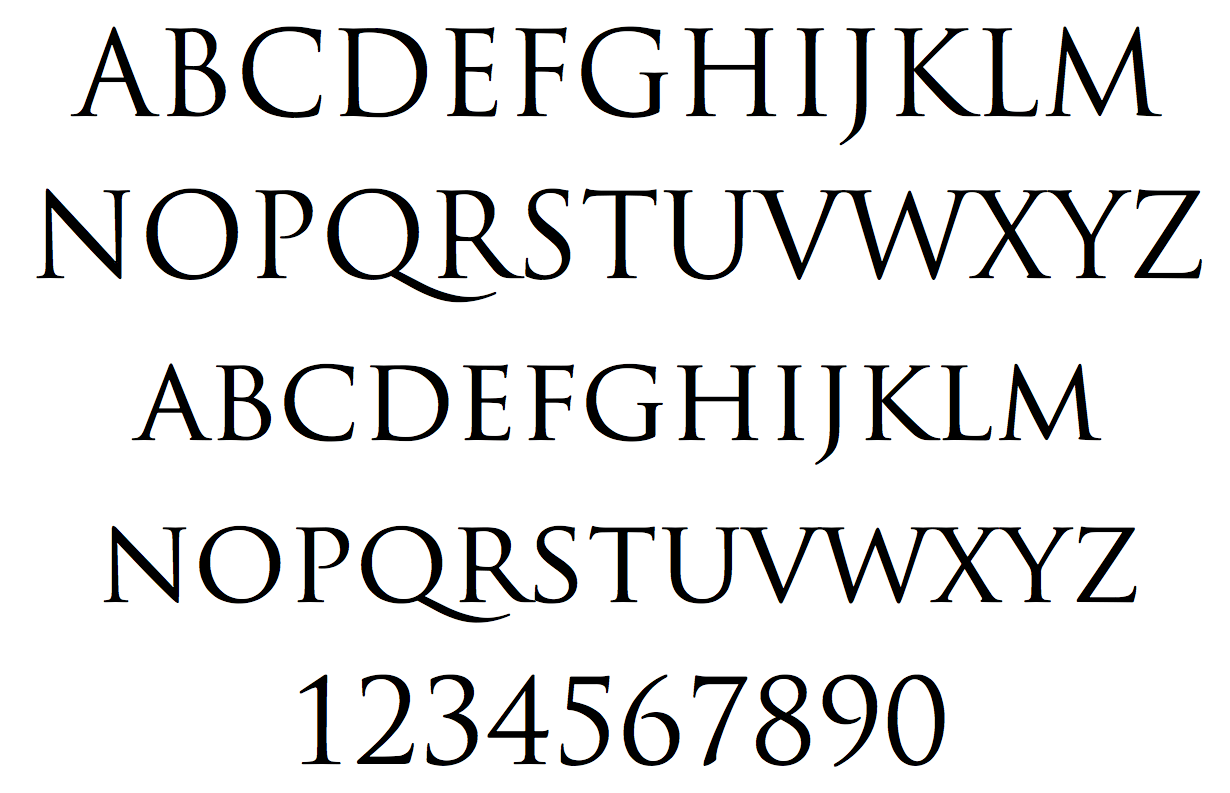
Borsok
Источник: vk.comАкцидентный шрифт от киргизского дизайнера Dastan Miraj
Ossem
Источник: vk.comГротеск в четырёх начертаниях, включающее обычное, округлое, грубое и ржавое начертания. Разработчик: Typedepot
Belepotan
Источник: vk.comАкцидентный шрифт, имитирующий написание кистью
Tangak
comАкцидентный шрифт от дизайнера Dastan Miraj
Cormac
Источник: vk.comГуманистический гротеск в двух начертаниях. Разработан в Typedepot
Akrobat
Источник: vk.comСовременный шрифт без засечек с сокращёнными пропорциями. Включает 8 начертаний, стилистические альтернативы, локализованные формы, табличные цифры. Разработчик: Fontfabric
Pomidorko
Источник: vk.comКириллический шрифт, который изначально создавался для оформления ютуб-канала PomidorKo. Автор: Тони Сидачова (Киев, Украина)
Exo 2.0
Источник: vk.comСовременный геометрический гротеск с технологическим чувством, сохраняющий при этом элегантность. Автор: Natanael Gama
Cormorant
Источник: vk.comЭкстравагантная антиква с большим количеством начертаний. Автор: Christian Thalmann (Цюрих, Швейцария)
Jazz Ball
Источник: vk.comБесплатный шрифт от Кирилла Михайлова в двух начертаниях
Paint-it-dark, Paint-it-goth, Paint-it-pagan
com Источник: vk.comCunia
Источник: vk.comАкцидентный шрифт Cunia с закругленными углами. Автор: Alejo Bergmann (Аргентина), студия Rostype. Кириллица: Денис Игнатов
Pelmeshka
Источник: vk.comАкцидентная антиква от Кирилла Михайлова
Первой пост я хочу посвятить 5 крутых летних рукописных шрифтов с кириллицей, на мой взгляд они крутые.
1. Шрифт House Movements Sign кириллица
Первый шрифт который открывает данную подборку , это шрифт House Movements Sign. Официально он не поддерживает кириллицу и перевели его наши русские дизайнеры.
шрифт House Movements Sign с кириллицей
2. Шрифт Brusher кириллицаВторой шрифт Brusher от графического дизайнера Влада Кристи.
шрифт Brusher кириллица
3. Шрифт Iced Tea кириллицаТретий шрифт Iced Tea от дизайнера Amy Cox. Шрифт получился очень сказочным, как будто сделан специально для детских книжек.
Шрифт Iced Tea кириллица
4. Шрифт Tangak кириллицаШрифт Tangak разработан киргирским дизайнером Dastan Miraj.
Шрифт отлично подойдет для больших заголовок. Если вы ведете блог или пишите посты в социальных сетях, то данный шрифт будет вам очень полезен. Он полностью бесплатный, а это говорит о полной свободе в использование.
Шрифт Tangak кириллица
5. Шрифт Celestina кириллицаШрифт разработан дизайнером Антониной Жулковой из Санкт Петербурга. Девушка хотела создать что то легкое и свободное. У нее получилось, легкий и воздушный шрифт Celestina, скачивайте и используйте его абсолютно бесплатно.
Когда девушка работала над шрифтом, её кошка Селестина очень был интересен процесс рисования кистью, что повлияло на названия шрифта)
Шрифт Celestina кириллица